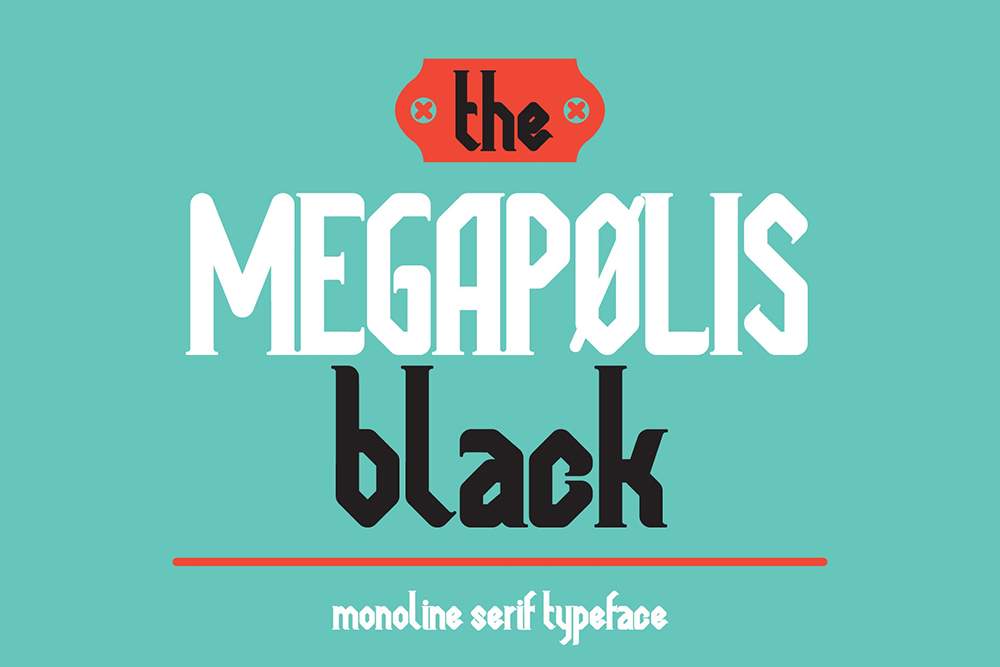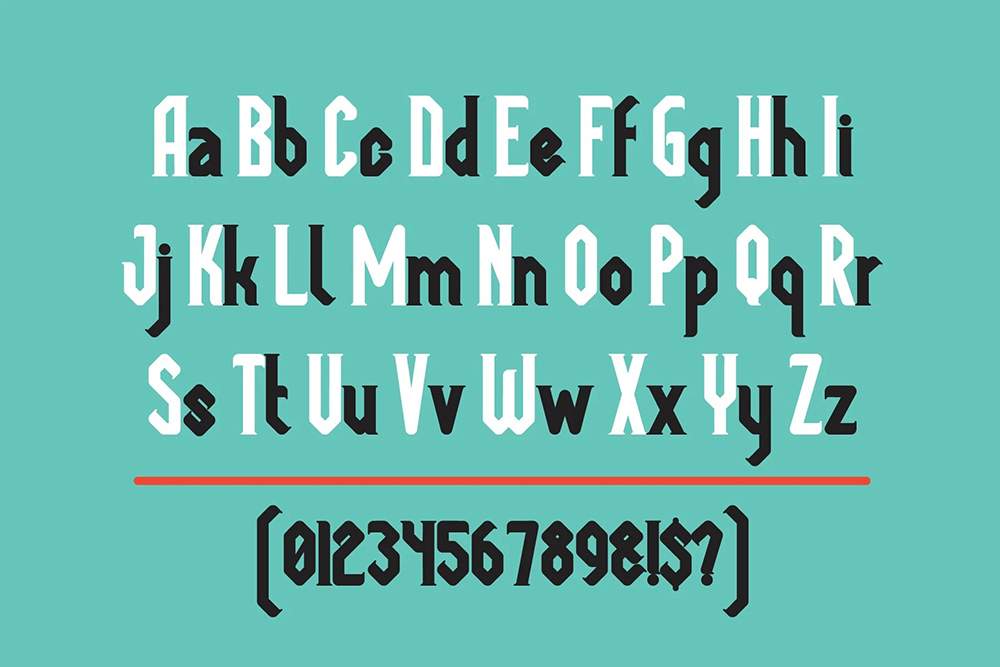
فونت پرمیوم و انگلیسی Megapolis Black Font یک فونت سریف تکخطی با ظاهری رترو است. Megapolis Black برای طراحی لوگو، هدر وبسایت، طراحی کارت عروسی، فونتهای منو برای وبسایت، طراحی مد و… مناسب است.
مزایای استفاده از فونت لاتین Megapolis Black چیست؟